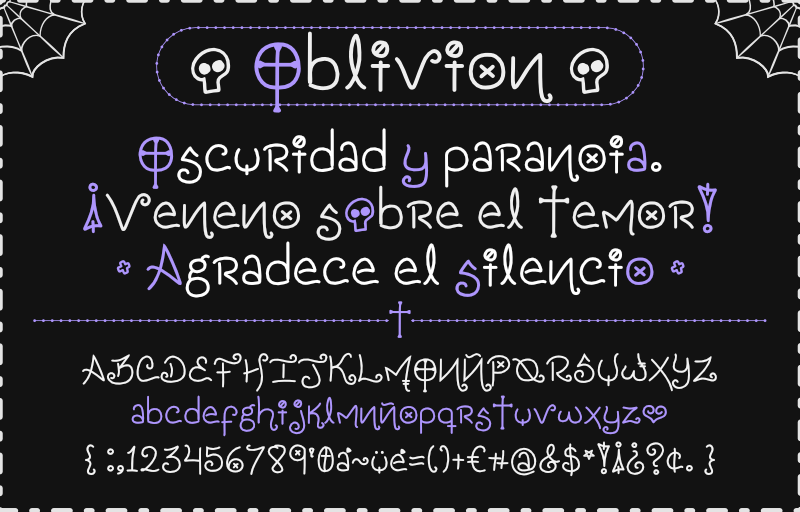
Esta font se basa en mi tipo de letra al escribir t�tulos. Con este signo "☺" puedes sustituir la -o- min�scula con una calavera. 🕷 EST� PERMITIDO: � Utilizarla con prop�sitos personales. � Redistribuirla. � Utilizarla con fines comerciales. � Incrustarla en un documento o convertirla a curvas. � Modificar sus proporciones. La atribuci�n no es necesaria si se utiliza en im�genes, videos o imprimibles. ~ ~ 💀 ~ ~ This font is based on my typeface when I write titles. With this sign "☺" you can replace the lowercase -o- with a skull. 🕷 IS ALLOWED: � Use it for personal purposes. � Redistribute it. � Use it for commercial purposes. � Embed in a document or convert to curves. � Modify its proportions. Attribution is not necessary if used in images, videos or printables. |